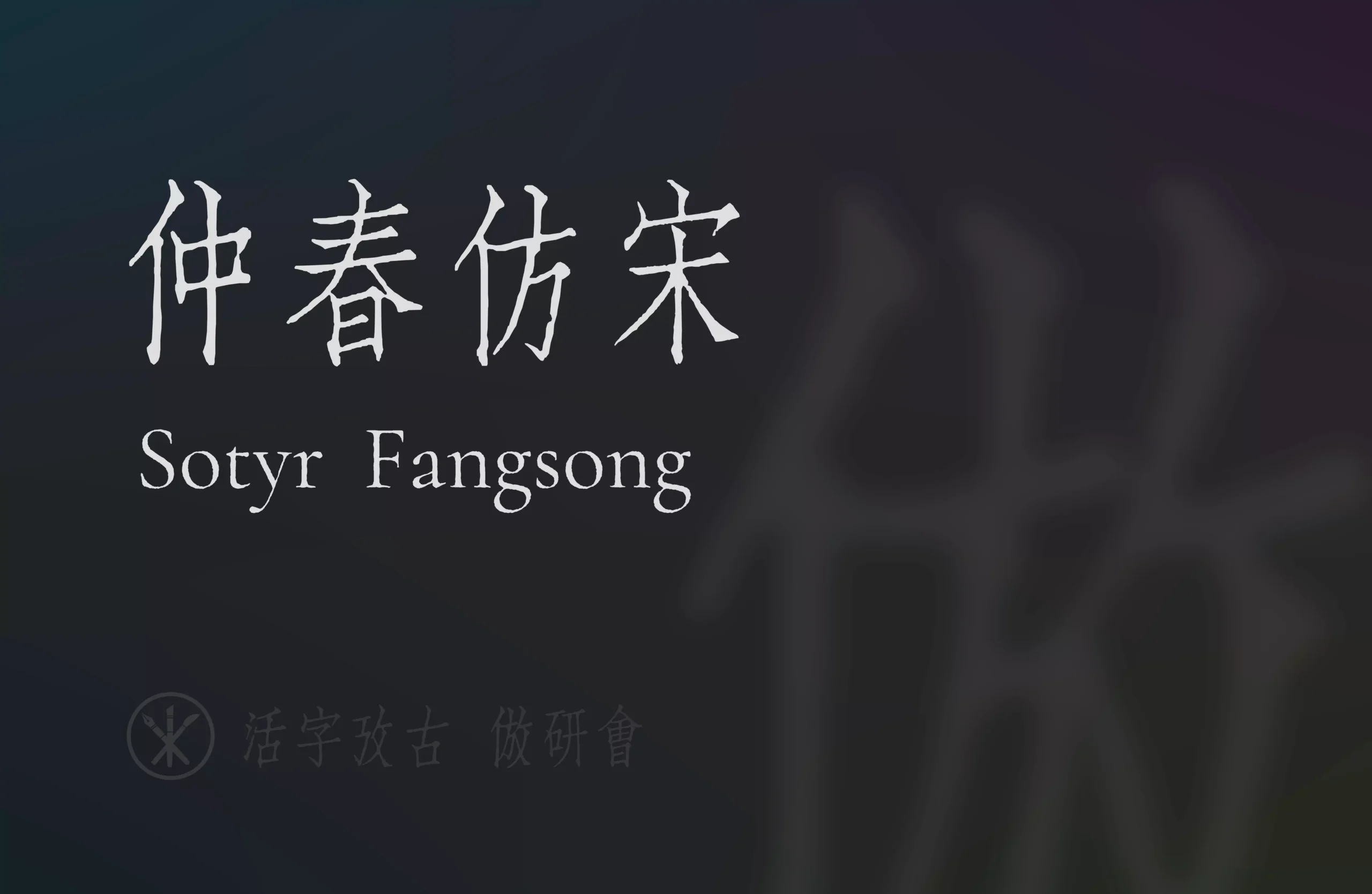
「仲春仿宋」项目是对上世纪聚珍仿宋二号长体铅活字字形进行的数字化。采用直接复刻办法,从印刷品扫描件中提取字形并封装为字体。
项目尚处于开发和测试阶段,其中的缺字、丑字不少,远不及正式版发布的程度。简化字部分是基本没有的,也不太推荐用于现代汉语文本的排版,还请各界朋友多多包涵。
开发故事
若论哪套长体仿宋最为著名?熟谙近现代印刷史的同志,恐怕大都会脱口而出「聚珍仿宋」。不过聚珍仿宋的长体铅字自身又包含多种字号,哪一种最具代表性?这个问题的答案或许在同志们的脑海中能浮现出,但落实到具体字号层面,就不那么好回答了。
聚珍仿宋二号长体铅字,造型妍美多姿,而又因其字号适中,常应用于正文排版而不是标题和夹注。相比于头号字的直健、三号四号字的间架异化处理、五号字的细密,二号字的字形可以说是最丰富地展现了聚珍仿宋家族的风味。同时,上世纪末,聚珍仿宋二号长体经过史云鹏的大力推广,成为了工程类制图常用的手写体。工科出身的朋友们,你们当年有没有练习过呢?
聚珍的头号方体长体、二号方体,市面已有产品,而尚无二号长体产品可用。
在印刷品样本方面,现在开放的电子化扫描件非常多了,缺少的只是对其中的字形进行提取封装的工作。这个工作量不小,所以从今年(2025)1 月开始,我们又合作开发了一种切片工具和一种封装前处理工具,效率大为提升,小组内的同志们拊掌称奇。
总之,「仲春仿宋」是传统汉字美学、印刷和数字化技术、新生产力结合的产物。
问:「为什么要叫『仲春』」呢?
答:这个项目是乙巳年仲春开始进行的。此外「仲」有「排行第二」的意思,而「春」的声符「屯」又有「聚集」的意思;二者结合,与「聚珍二号」暗应。「Sotyr」是「聚珍」的谐声域。
此次发布的 v0.16-beta 是仲春仿宋的第二个公开测试版,经过一个多月痛苦的修字终于得以跟朋友们见面。
此次更新的主要内容为:
- 增加简入繁出版本,可以便利惯用简化字的用户。这份简入繁出的文件是通过 TCFontCreator 生成的,部分缺少的字使用了罕见的异体字进行替换,使用时需要注意。
SotyrFangsong-S2T-Regular即为简入繁出版。 - 新切了二十余本书籍,扩展了辖字数量。其中对《新曲苑》的采样,增加了大量白话文用字。
- 修饬了大量在上个版本中印糊、缺墨、歪斜等的丑字。
- 略微加粗西文、数字、西文标点。
- 统一了中日韩标点的字形风格。